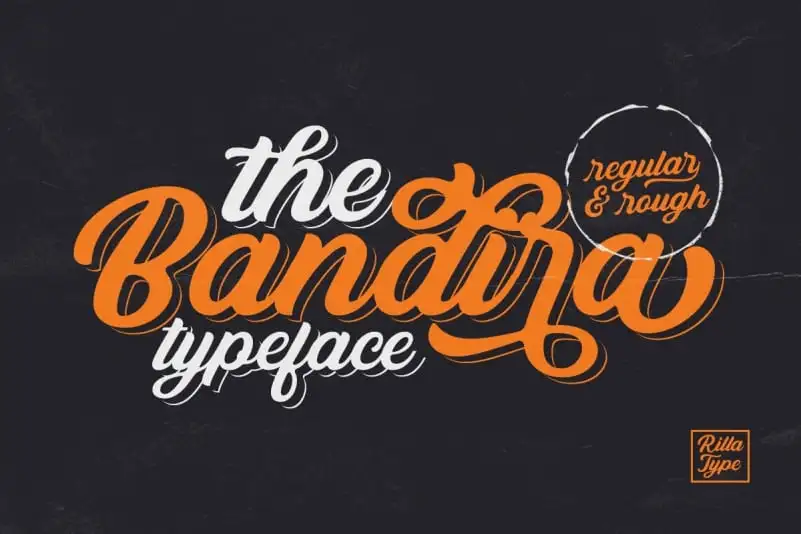
Bandira Script Font
A Bandira Script Font é uma elegante tipografia escrita à mão ideal para criações de logotipos, roupas, convites, marcas, embalagens e propaganda. Seu design bold e refinado oferece um ar autêntico que é perfeito para quem precisa de um tipo específico para esses projetos. Este tipo digital vem em letras maiúsculas e minúsculas, sinais ortográficos, símbolos e números, além de seis conjuntos alternativos de estilização, ligações, e swashes. A Bandira ainda suporta múltiplas línguas e está codificada PUA (Unicode), permitindo que você aceda ao swash simplesmente inserindo ‘_1’ ou ‘_3’ no final da palavra, por exemplo: Bandira_1 ou Bandira_3. Com uma aparência única e sofisticada, a Bandira Script Font se destaca como um recurso valioso para designers de multimídia que procuram adicionar detalhes elegantes aos seus projetos. O design cuidadoso da fonte oferece uma experiência visual interessante que pode ser usada em diferentes tipos de projetos, garantindo que você encontre a melhor opção para seu próximo projeto criativo.